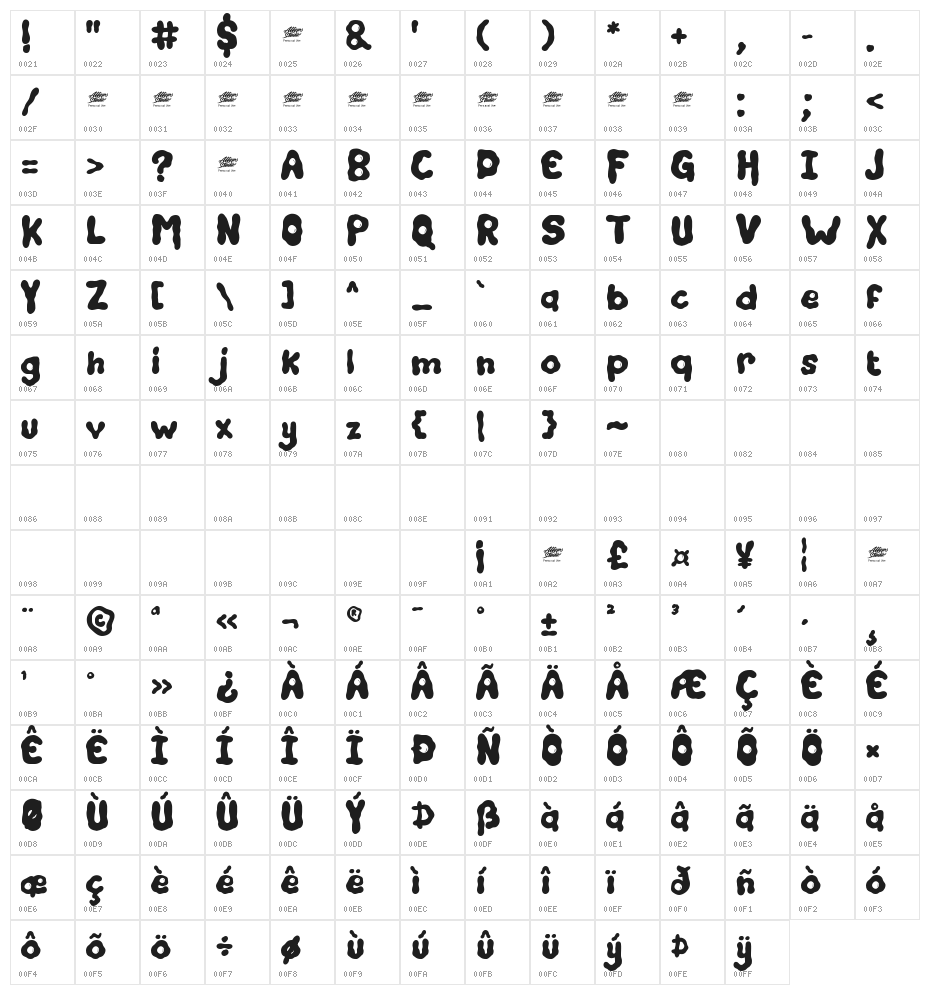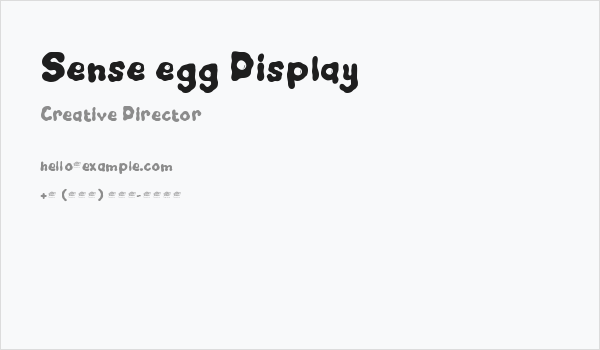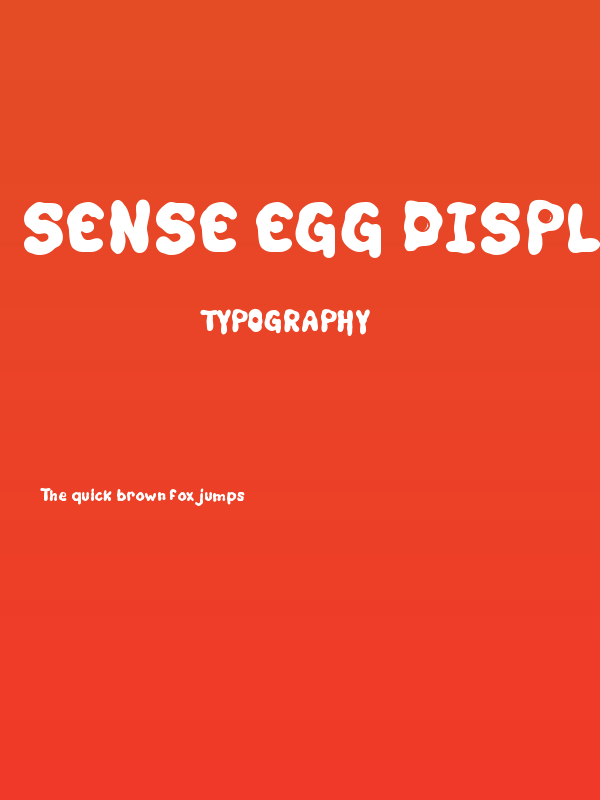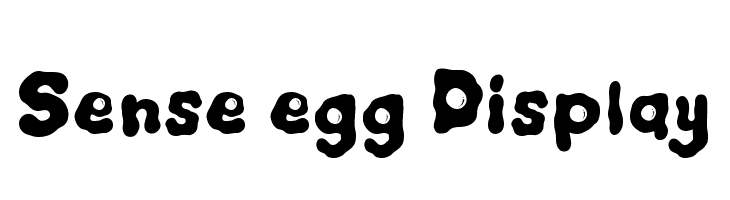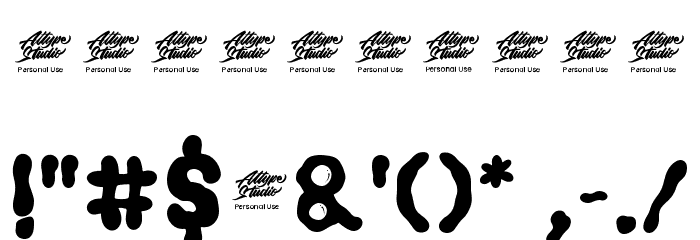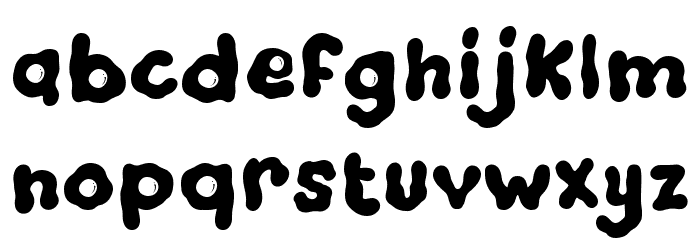
Sense egg Display Font
| 全体的なスタイル | Playful, Whimsical |
| 用途 | Logos, Posters, Invitations |
| おすすめプロジェクト | Ideal for children's books, playful branding, party invitations, and creative posters. |